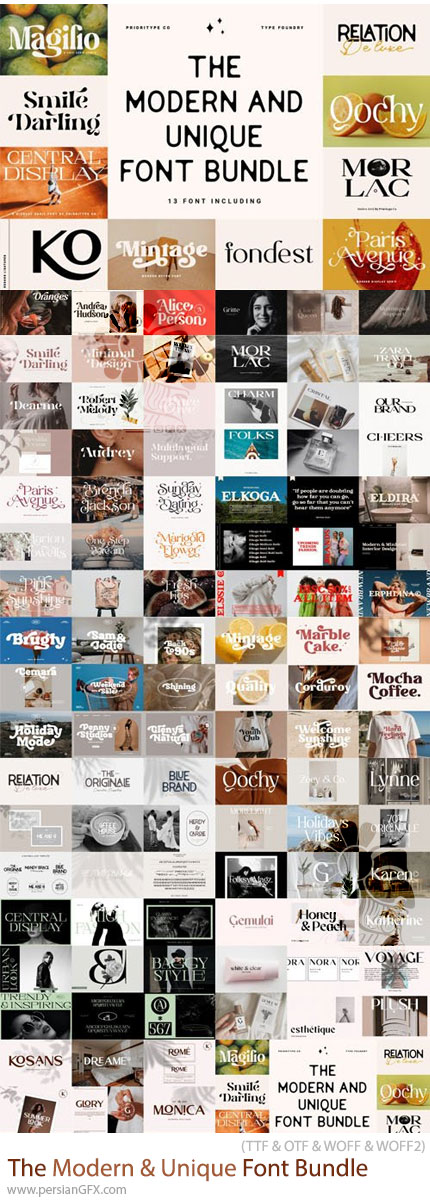
The Modern & Unique Font Bundle مجموعهای از 13 فونت پریمیوم و مدرن است که برای طراحان گرافیک، طراحان برند، تولیدکنندگان محتوا و افرادی که به دنبال فونتهای متفاوت برای پروژههای خلاقانه هستند، تهیه شده است و با فرمت های OTF و TTF و WOFF و WOFF2 بر روی سایت برای دانلود قرار گرفته است. این مجموعه میتواند برای ایجاد هویت بصری، لوگوتایپ، پوستر، تبلیغات، طراحی شبکههای اجتماعی، بستهبندی و پروژههای چاپی و دیجیتال مورد استفاده قرار گیرد و با در اختیار داشتن چندین سبک فونت، گزینههای متنوعی برای انتخاب تایپوگرافی در اختیار شما قرار میدهد. داشتن یک مجموعه متنوع از فونتهای مدرن میتواند فرآیند انتخاب تایپوگرافی را برای پروژههای مختلف سادهتر کند. بسته به نوع طراحی، میتوانید از فونتهای این مجموعه برای ایجاد تیترهای قدرتمند، نوشتههای مینیمال، طراحیهای مدرن و عناصر بصری متمایز استفاده کنید. این پک فونت یک مجموعه شامل 13 فونت مدرن و منحصربهفرد برای توسعه پروژههای گرافیکی، برندینگ، تبلیغات و تایپوگرافی است. این بسته با ارائه سبکهای متنوع میتواند به طراحان کمک کند تا برای هر پروژه، فونت مناسبتری انتخاب کرده و ظاهر بصری حرفهایتر و متمایزتری ایجاد کنند.
ویژگیهای مجموعه:
- شامل 13 فونت حرفهای و پریمیوم
- طراحی مدرن و خلاقانه
- مناسب برای پروژههای گرافیکی متنوع
- مناسب برای طراحی برند و هویت بصری
- کاربردی برای تایپوگرافی و طراحی تبلیغاتی
- مناسب برای پروژههای چاپی و دیجیتال
- قابل استفاده در نرمافزارهای مختلف طراحی
- مناسب برای ایجاد تیترها و نوشتههای چشمگیر
کاربردهای فونتها:
از این مجموعه میتوان در پروژههایی مانند:
- طراحی لوگو و لوگوتایپ
- هویت بصری برند
- طراحی پوستر
- طراحی بروشور و فلایر
- تبلیغات
- طراحی بستهبندی
- پست و استوری شبکههای اجتماعی
- طراحی کاور
- مجلات و نشریات
- طراحی تیشرت و محصولات چاپی
- کارت و دعوتنامه
- تایپوگرافی خلاقانه
- پروژههای گرافیکی و هنری
مناسب برای:
- طراحان گرافیک
- طراحان برند و هویت بصری
- طراحان لوگو
- طراحان تبلیغات
- طراحان شبکههای اجتماعی
- فریلنسرها
- طراحان بستهبندی
- علاقهمندان به تایپوگرافی
- تولیدکنندگان محتوای بصری